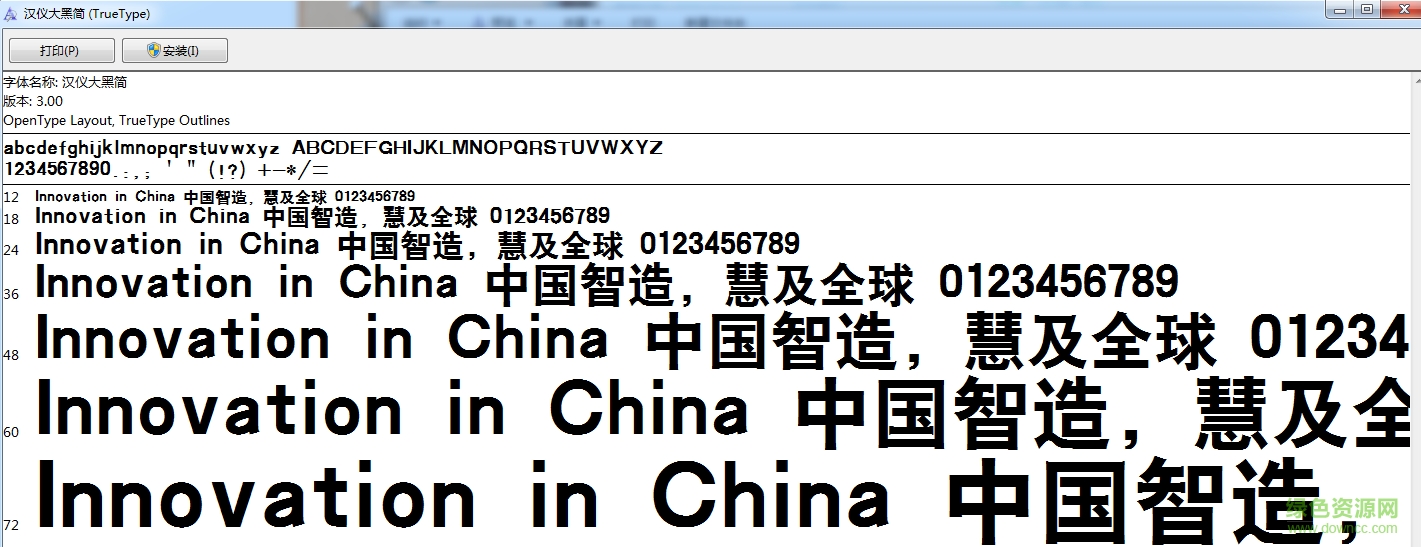
漢儀大黑簡
漢儀大黑簡體字體是一款很有厚重莊嚴感的漢儀字體,使用于正規(guī)場合的設計排版需要,本字體支持所有windows系統(tǒng)和蘋果MAC系統(tǒng),歡迎大家下載體驗!
漢儀大黑簡介紹
漢儀大黑簡字體樸素大方、結(jié)構(gòu)嚴謹,非常引人注目,常用作印刷中穩(wěn)重、醒目的標題字。